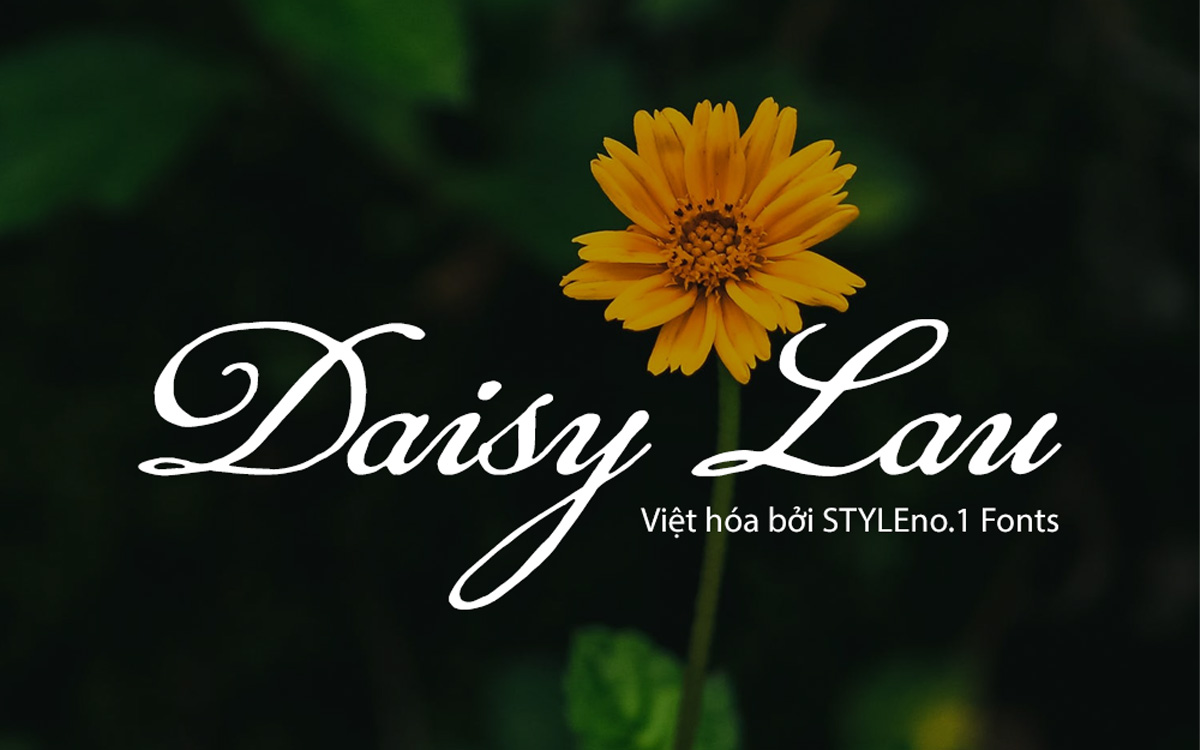
Font Chữ Viết Tay SVN Daisy Lau Việt Hoá
Font Chữ Viết Tay SVN Daisy Lau Việt Hoá là một lựa chọn nổi bật dành cho những ai yêu thích phong cách chữ viết tay mềm mại, tự nhiên và giàu cảm xúc. Với đường nét uyển chuyển, gần gũi cùng khả năng hiển thị tiếng Việt đầy đủ, font chữ này phù hợp để tạo điểm nhấn cho nhiều sản phẩm thiết kế như thiệp mời, logo, bao bì, bài đăng mạng xã hội, tiêu đề và các ấn phẩm mang phong cách cá nhân.
Không chỉ tạo cảm giác như được viết bằng tay, SVN Daisy Lau còn giúp nội dung trở nên thân thiện, sinh động và dễ ghi nhớ hơn. Đây là một gợi ý đáng cân nhắc cho nhà thiết kế, người sáng tạo nội dung, chủ shop, đơn vị in ấn hoặc bất kỳ ai đang tìm kiếm một font chữ viết tay Việt hoá có tính ứng dụng cao.
Font Chữ Viết Tay SVN Daisy Lau Việt Hoá Mềm Mại, Tự Nhiên Và Đầy Cảm Xúc
Font Chữ Viết Tay SVN Daisy Lau Việt Hoá gây ấn tượng nhờ phong cách chữ phóng khoáng nhưng vẫn giữ được sự hài hòa cần thiết trong thiết kế. Các ký tự được xây dựng theo tinh thần của chữ viết tay hiện đại, mang đến cảm giác chân thành, gần gũi và có dấu ấn cá nhân. Khi sử dụng đúng bối cảnh, font chữ có thể biến một dòng tiêu đề đơn giản thành điểm nhấn giàu cảm xúc, giúp thiết kế nổi bật mà không cần bổ sung quá nhiều chi tiết trang trí.
Phiên bản Việt hoá hỗ trợ hệ thống dấu tiếng Việt, giúp người dùng thuận tiện hơn khi trình bày nội dung có dấu. Những câu chúc, tên thương hiệu, thông điệp quảng cáo hoặc nội dung dành cho khách hàng Việt Nam có thể được thể hiện đồng bộ, hạn chế tình trạng thiếu ký tự hoặc lỗi dấu thường gặp ở một số font nước ngoài chưa được tối ưu.
Hỗ trợ tiếng Việt đầy đủ và thuận tiện khi soạn thảo
Một trong những ưu điểm quan trọng của SVN Daisy Lau Việt Hoá là khả năng hiển thị các ký tự tiếng Việt. Font có thể đáp ứng những nguyên âm đặc trưng như ă, â, ê, ô, ơ, ư cùng hệ thống dấu thanh, nhờ đó người dùng dễ dàng viết tên riêng, câu slogan, lời chúc hoặc nội dung quảng cáo bằng tiếng Việt.
Khả năng hỗ trợ dấu giúp thiết kế duy trì sự thống nhất về kiểu chữ, thay vì phải thay thế ký tự lỗi bằng một font khác. Điều này đặc biệt hữu ích khi thiết kế logo dạng chữ, thiệp cưới, thiệp sinh nhật, thực đơn, bảng giá, nhãn sản phẩm hoặc nội dung truyền thông cần sự chỉn chu. Để đạt kết quả tốt nhất, người dùng nên kiểm tra toàn bộ câu chữ sau khi nhập, nhất là với các phần mềm hoặc bộ gõ có thiết lập bảng mã khác nhau.
Phong cách viết tay mềm mại, gần gũi và có dấu ấn riêng
SVN Daisy Lau mang vẻ đẹp của nét chữ viết tay với những đường cong tự nhiên, tạo cảm giác nhẹ nhàng và giàu tính thủ công. Phong cách này phù hợp với các thiết kế cần truyền tải sự thân thiện, lãng mạn, nữ tính hoặc tinh tế. So với những font chữ hình học cứng cáp, font viết tay thường tạo ra kết nối cảm xúc rõ ràng hơn, khiến thông điệp giống như một lời nhắn được viết riêng cho người xem.
Font có thể được sử dụng cho tiêu đề ngắn, tên sản phẩm, chữ ký thương hiệu, câu trích dẫn hoặc các từ khóa cần nhấn mạnh. Trong quá trình dàn trang, bạn có thể kết hợp SVN Daisy Lau với một font không chân đơn giản cho phần nội dung dài. Cách phối hợp này vừa giữ được nét cá tính ở tiêu đề, vừa bảo đảm khả năng đọc và tạo sự cân bằng cho tổng thể thiết kế.
Ứng dụng linh hoạt trong thiết kế cá nhân và truyền thông
Nhờ vẻ ngoài giàu cảm xúc, Font Chữ Viết Tay SVN Daisy Lau Việt Hoá có thể được ứng dụng trong nhiều nhóm sản phẩm khác nhau. Từ thiết kế trực tuyến đến ấn phẩm in, font chữ giúp nội dung trở nên mềm mại và dễ tạo thiện cảm với người xem. Một số ứng dụng tiêu biểu gồm:
• Thiết kế thiệp cưới, thiệp sinh nhật, thiệp cảm ơn, thiệp chúc mừng và thư mời sự kiện.
• Tạo logo dạng chữ, tên thương hiệu, chữ ký cá nhân hoặc dấu hiệu nhận diện cho cửa hàng.
• Trang trí bao bì mỹ phẩm, nến thơm, đồ thủ công, thời trang, phụ kiện và sản phẩm quà tặng.
• Thiết kế poster, banner, ảnh bìa, bài đăng Facebook, Instagram, TikTok và nội dung quảng cáo.
• Trình bày câu trích dẫn, tiêu đề video, bìa sách, sổ tay, menu hoặc bảng giá dịch vụ.
Tuy có phạm vi ứng dụng rộng, font chữ viết tay thường phát huy hiệu quả cao nhất ở những đoạn nội dung ngắn hoặc kích thước chữ đủ lớn. Với phần văn bản dài, người dùng nên ưu tiên font có cấu trúc đơn giản và dễ đọc hơn, sau đó dùng SVN Daisy Lau làm điểm nhấn. Cách sử dụng có chọn lọc sẽ giúp bố cục chuyên nghiệp, tránh cảm giác rối mắt hoặc làm giảm độ rõ của thông tin.
Dễ kết hợp với nhiều phong cách thiết kế
SVN Daisy Lau có thể xuất hiện trong cả thiết kế tối giản lẫn bố cục trang trí nhiều lớp. Khi đặt trên nền sáng với bảng màu pastel, font tạo cảm giác nhẹ nhàng, thanh lịch và lãng mạn. Khi kết hợp với màu sắc tương phản, hình khối mạnh hoặc ảnh sản phẩm, font lại trở thành một chi tiết cân bằng, giúp thiết kế bớt khô cứng và gần gũi hơn.
Để xây dựng một bố cục hài hòa, người dùng có thể áp dụng một số nguyên tắc cơ bản:
1. Sử dụng font cho tiêu đề, tên thương hiệu hoặc thông điệp chính thay vì toàn bộ nội dung.